글자는 보이지 않는 공기처럼_하라 켄야
<디자인의 디자인>, <白> 등의 저서와 무인양품(MUJI) 아트 디렉터로 잘 알려진 일본의 대표적인 그래픽디자이너 하라 켄야(Hara Kenya)가 한국을 다녀갔다. 2013년 서울에서 펼쳐질 <타이포잔치 : 서울 국제 타이포그래피 비엔날레>에 앞서 <타이포잔치 사이사이> 사전행사를 통해 대중강연회가 진행된 것. 그 중 하라 켄야의 강연 내용을 인터뷰 형식으로 정리해 소개한다.
최근에 진행 중인 작업부터 소개해주세요.
오랫동안 존경해온 안상수 선생님 도움으로 한국 디자이너 여러분과 만날 수 있게 되었습니다. 감사합니다. 우선, 최근에 관여하고 있는 <Architecture for Dogs>(http://architecturefordogs.com)라는 개(dog)를 위한 건축 프로젝트를 소개합니다. 저를 포함해 시게루 반, 카즈요 세지마, 켄고 쿠마 등 일본 건축가와 세계적인 건축가들이 참여해 진행되고 있는데요. 이 프로젝트는 단순히 ‘개집’을 만드는 작업이 아닙니다. 잘 아시다시피 개는 야생 늑대에서 오랜 시간 진화를 거듭해 인간과 함께 생활하며, 우리 곁에 남게 된 친숙한 동물 중 하나입니다. 인간이 없었다면 오늘 우리가 대하는 개는 지금의 모습이 아니었겠죠. 이제 와서 야생으로 돌려보낼 수도 없는 상황이고요.
그런데 문제는 지금까지 인간의 시선과 스케일로 개들이 생활하고 살아가는 환경을 만들어왔다는 점입니다. 우리와 함께 호흡하는 동물에 맞는 스케일은 고려하지 않았던 것이죠. 저는 인간의 스케일에서 벗어나 개를 위한 스케일에 집중했습니다. 인간 스케일에서 개를 위한 스케일로 기존의 동물 가구와 의류 디자인 등을 바꿔나가면 인간과 동물의 관계가 지금보다 더 좋게 변화할 수 있다는 생각에서 출발합니다. 개는 전세계적으로 사랑 받는 동물이기 때문에 개를 위한 건축 아이디어는 세계적으로 퍼져나갈 수도 있겠죠. 올해 12월에 마이에미에서 처음 오픈하고 2013년 가을에는 도쿄에서 공개될 예정입니다. 물론, 한국에서도 가능하겠죠.
<Architecture for Dogs>
<白>, <디자인의 디자인> 등의 저서를 통해 선생님의 디자인 철학은 이미 많이 알려져 있는데요. 간단하게 설명 부탁 드립니다.
저와 제 팀이 작업해온 디자인을 보면 아시겠지만 대체로 미니멀(minimal) 합니다. 북디자인을 할 때도 마찬가지인데요. 저는 지금도 그리드 시스템(Grid System)을 활용합니다. 저 같은 디자이너에게 그리드 시스템은 굉장히 유용한 도구 중 하나입니다. 1920년대에 처음 도입된 그리드 시스템에 고마워하고 있죠. (웃음) 특히나 일본어와 중국어, 영어와 한글 등이 함께 들어가야 하는 디자인에서는 그리드가 그 기능을 잘 해냅니다. 기본적으로 저는 어떤 컨텐츠를 보여주고자 할 때 글자는 ‘공기’처럼 사라져버리는 게 좋다는 생각으로 작업합니다. 북디자인이든 술 패키지든 디자인에 들어가는 글자는 언제나 최소한으로, 반면에 의미는 강하게 전달될 수 있도록 노력하죠 ‘심플(simple)’이 아니라 ‘텅빈(empty)’ 느낌을 생각하시면 됩니다. 메시지를 강하게 던지지 않고 상대가 그 이미지를 자연스럽게 받아들이도록 하는 것입니다. 텅 빈 그릇을 만들어 그들과 커뮤니케이션 해나가는 방식이죠.
2011년 일본에서 발생한 대지진과 원전사고 데이터를 그래프로 정리하는 작업을 진행했습니다. 그때 우리가 정한 디자인 기준은 네 가지였습니다. 첫째, 연출하지 않는다. 둘째, 주장하지 않는다. 셋째, 누구든 알아보기 쉽게 표현한다. 넷째, 가능한 정확하게 디자인한다. 과장된 표현은 지양하고 311 때 어떤 일이 어떻게 얼마나 일어났는지 정확하게 전달하는 것에 집중했습니다. 그러자 의도하지 않았던 아름다움이 표출되었죠. 이 기준들은 제가 생각하는 타이포그래피와 맥락이 같습니다. 제 디자인의 기축이 되는 지점이죠. 디자이너는 타이포그래피를 위한 타이포그래피를 해서는 안됩니다. 디자이너가 아닌 사람이 보더라도 글자들은 디자인에 공기처럼 녹아 들어 있어야 하고, 의식되거나 거슬리지 않아야 합니다. 그때 타이포그래피의 큰 힘이 나온다고 생각합니다.
술 패키지 디자인과 북디자인 작업
311 대지진과 후쿠시마 원전사고 데이터를 정리한 디자인 작업
기억에 남는 프로젝트가 있으면 소개해 주세요. 타이포그래피와 관련해 말씀해주시면 좋겠습니다.
오랜 시간 무인양품 아트디렉터로 활동했습니다. 쓸데없는 것들은 과감하게 버리며 디자인했습니다. 디자인 의도, 디자인 하려는 디자이너의 기분을 들키는 건 부끄러운 일입니다. 디자이너의 의도가 명확하게 드러나는 건 좋지 않다고 생각합니다. 유행이나 트렌드에 의지하는 것도 바람직하지 않죠. 무인양품과 작업할 때에도 가능한 유행에 편승하지 않으면서 디자인 의도가 보이지 않도록 노력했습니다. 중립적으로 글자를 사용했고 공기처럼 아무 것도 남아있지 않다는 느낌으로 타이포그래피를 적용했죠. 가능한 아무 것도 하지 않는 것, 디자인이 없는 것, 디자인 의도가 거의 느껴지지 않는 것. 무인양품은 그런 작업 중 하나입니다.
하라켄야가 아트디렉터로 참여한 무인양품 브랜드
제 작업들에 글자가 어떻게 들어가고 있는지 유심히 살펴보면 앞서 이야기한 내용을 이해하기 쉽습니다. 먼저, 츠타야 서점(Tsutaya Books)의 로고 디자인입니다. 츠타야 서점의 마케팅 타깃은 어린 아이보다는 성인들이기 때문에 튀는 디자인은 제 역할을 하지 못한다고 판단했습니다. 전체적으로 차분한 느낌이 들도록 디자인했습니다. 방문객 중엔 나이가 지긋한 어르신들도 많아 글자를 크게 키웠습니다. 대신 서점 안에서는 큰 글자가 필요 이상으로 공간을 차지할 수 있어 반투명으로 처리했습니다. 존재감은 있지만 방해되지 않도록 처리한 것이죠.
츠타야 서점(Tsutaya Books)
12년 전에 작업한 백화점 마츠야 긴자(Matsuya Ginza) 디자인도 비슷합니다. 제가 제안해 도트 패턴을 디자인 전반에 넣었습니다. 건물 외벽, 백화점 멤버십 카드, 포장지, 종이백 등에 모두 동일한 패턴을 넣고 그 특징을 살려 건축물과 타이포그래피를 연결했습니다. 그래픽 디자인과 타이포그래피, 건출물이 모두 하나의 패턴으로 일체가 되도록 했습니다.
Matsuya Ginza
글자디자인에도 관심이 많다고 들었습니다.
글자를 만들고 있습니다. 가능하면 가로와 세로가 균일하고, 두께 차이가 거의 없는 명조체와 고딕체의 중간 느낌을 살릴 생각입니다. 특징 없는 것이 특징이 되는 글자를 만들려고 합니다. 지금까지 제 작업들을 보면 아시겠지만 불필요한 요소는 최대한 제거하고 글자만 들어간 경우가 많습니다. 제 디자인을 알기 쉽게 만들기 위해서는 제 글자가 필요하다는 생각이 들었죠. 일본어는 생각보다 복잡합니다. 히라가나와 가타가나를 비롯해 한자와 영문, 숫자를 모두 포함하고 있죠. 타이포그래피 작업에는 다소 어려운 구조입니다. 하지만 이와 같은 마이너스적인 요소를 극복하고 해소해나갈 때 더 강해질 수 있다고 생각합니다. 일본이 언어적으로 어려운 환경이라 아시아 공동폰트라는 발상을 하게 되었을지도 모르겠네요. 우선, 일본어와 한자를 만들고 있는데 가능하면 동일한 컨셉으로 한글과 영문도 만들고 싶습니다. 일본에 머무르지 않고 아시아를 상대로 프로젝트를 진행하고 있기 때문에 일본어와 중국어, 한글이 모두 통일된 서체로 디자인이 이루어지면 그 효과가 배가될 것으로 전망하고 있습니다.
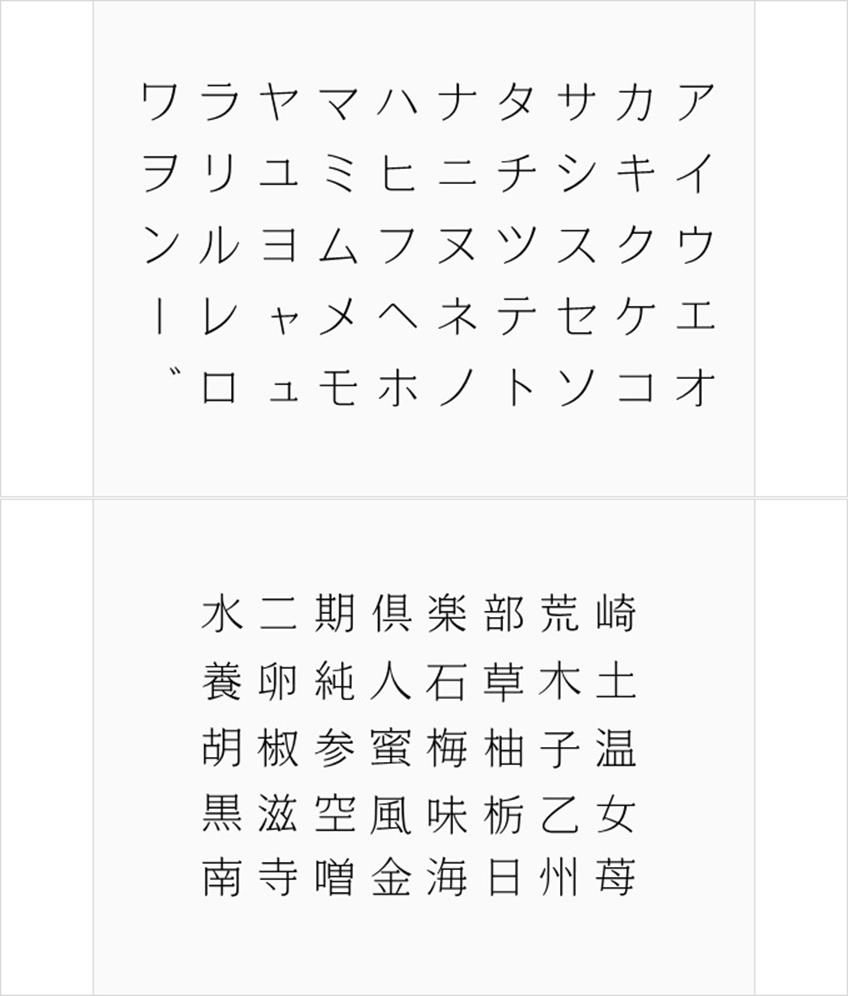
중국과 관련된 디자인 작업에서는 앞선 프로젝트들과는 다른 느낌입니다. 어떤 차이가 있나요?
앞에서 말씀 드린 ’empty’에 이어 밀도, 즉 ‘density’에 대한 이야기를 해야겠네요. 중국은 일본과 달리 밀도가 느껴지는 곳입니다. 제가 지금까지는 주로 비우는 작업을 해왔다면, 중국과 관련된 프로젝트에서는 채우는 것에 집중했습니다. <2008 북경올림픽> 지면 공모전을 위해 작업한 디자인이 대표적인 사례입니다. 중국의 상형문자를 기본으로 픽토그램을 만들었죠. 픽토그램이 조밀하고 밀도 있게 모이면 마크가 됩니다. 그림 글자가 원 안에 모인 것이죠. 도장이 되기도 하고 티켓이나 포스터 사인 시스템으로도 전개가 가능합니다. 아쉽게 1등이 아니라 2등 수상에 그친 작업이었지만 중국이 갖는 고유의 밀도감을 느끼고 학습할 수 있는 좋은 기회였죠. 이때 본격적으로 중국 디자인에 흥미를 느끼게 되었습니다.
2008 베이징올림픽 디자인 공모 작품
두 번째 작업은 중국의 ‘경덕진(景德鎭)’이라는 마을을 위한 프로젝트입니다. 중국 최대의 도자기 단지로도 유명한 곳입니다. 12가지 동물을 넣어 전통 문양을 현대적으로 재해석해 밀도가 느껴지는 문양을 디자인했습니다. 중국에서만 가능한 디자인이라고 생각합니다. 중국에는 도형 문양이 있는데 그들이 사용하는 글자와 관계가 있습니다. 또 하나의 작업은 중국 천안문 광장 근처에 있는 ‘대책란(大柵欄)’을 위한 프로젝트입니다. 중국의 전통미가 남아있는 작은 마을을 위한 작업인데요. 중국의 옛 거리가 그대로 보존된 곳입니다. 약 1.5km 주면 마을 곳곳을 3차원 데이터로 만들어 마을 내비게이션 시스템을 만들고 그 이미지를 바탕으로 마을의 아이덴티티를 표현했습니다. (앱 다운로드 http://bit.ly/118OJNo)
‘중국’하면 떠오르는 낡은 종이에 접목해 중국적인 느낌을 살리고, 아무리 파고 들어가도 끝없이 정보를 접할 수 있도록 데이터를 조밀하게 넣었죠. 3차원 지도를 2차원 지도로 만들고 그 지도 이미지를 기반으로 손수건, 티셔츠, 쇼핑 봉투 등을 제작해 관광 상품으로 활용합니다. 함께 개발된 애플리케이션은 관광객들이 스마트 기기를 이용해 대책란 거리 정보를 손쉽게 확인하도록 도와줍니다. 이 프로젝트를 통해 대책란 거리가 많은 이들에게 널리 알려지면서 고층 건물을 올리려는 개발 사업으로부터 마을이 보호받을 수 있길 기대해봅니다.
디자인 영역이 재미있어지기 위해서는 산업이 재미있어야 합니다. 재미있지 않으면 의미가 없다고 생각합니다. 경기가 좋으면 디자인은 멋있는 척만 하면 되지만, 경기가 좋지 않을 땐 새로운 가치를 제시하고 새로운 산업의 가능성을 가시화해야 합니다. 이런 건 어떤지, 이렇게 하면 어떠한지 구체적인 형태로 제시하는 것도 디자이너의 역할입니다. 새로운 산업의 가능성을 ‘가시화(visualizing)’ 하는 것이죠. <하우스 비전>도 그런 맥락에서 시작되었습니다. 한국에서도 공유 가능한 내용입니다. 함께 생각하며 발전시켜가면 좋겠습니다. 3월에 뵙겠습니다. 감사합니다.
하우스비전(http://house-vision.jp) 사이트와 기자회견 현장